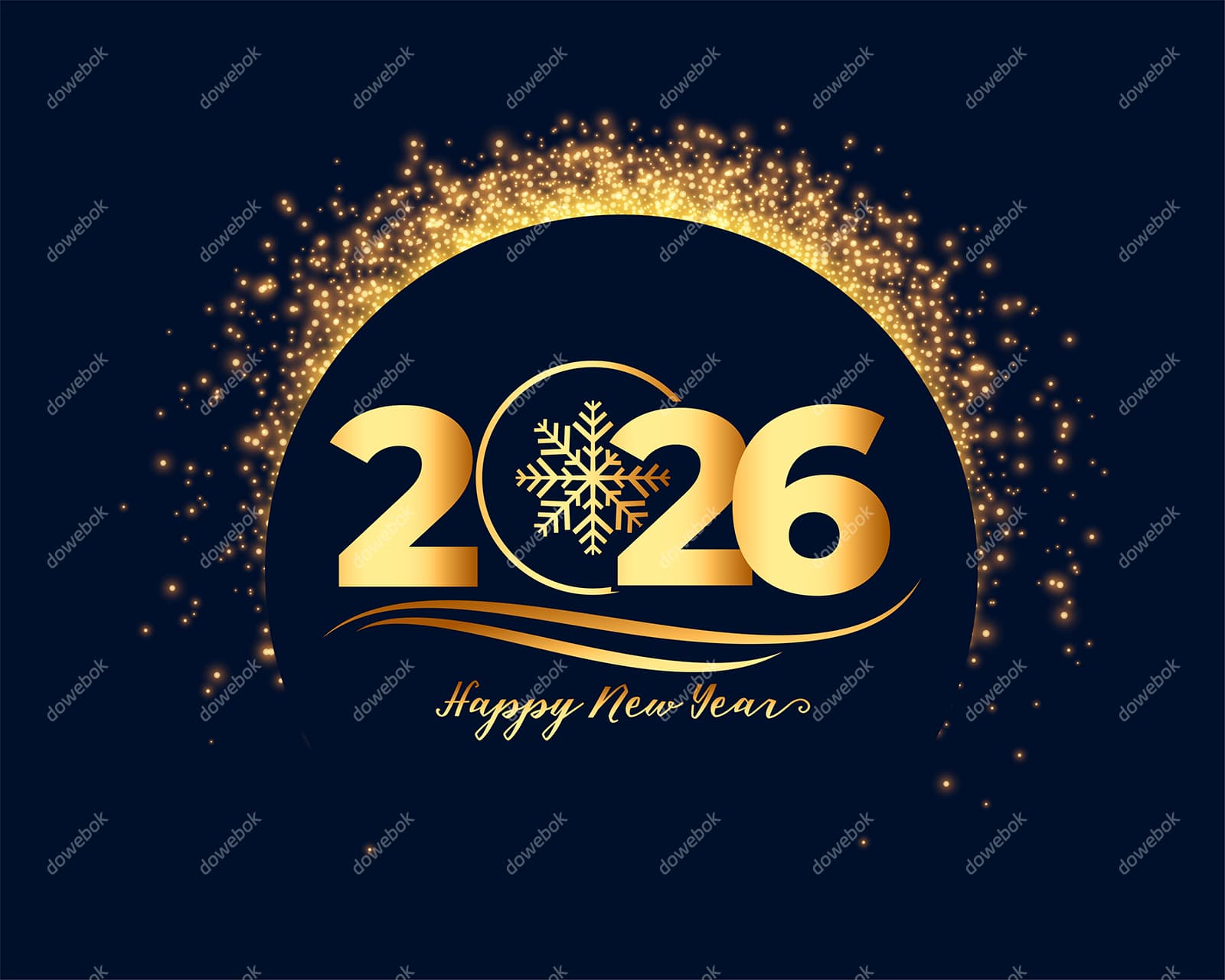
这是一款金色星点和金色数字设计 2026 新年快乐矢量素材,深幽藏青背景上,金色光斑聚成弧形光晕,似烟花漫散。中间 “2026” 以鎏金立体呈现,数字 “0” 嵌着雪花装饰,精致亮眼。下方衬着柔美的金色花体 “Happy New Year”,整体以冷调底色配暖金元素,既显冬日跨年的氛围感,又透出轻奢华丽的节日质感。